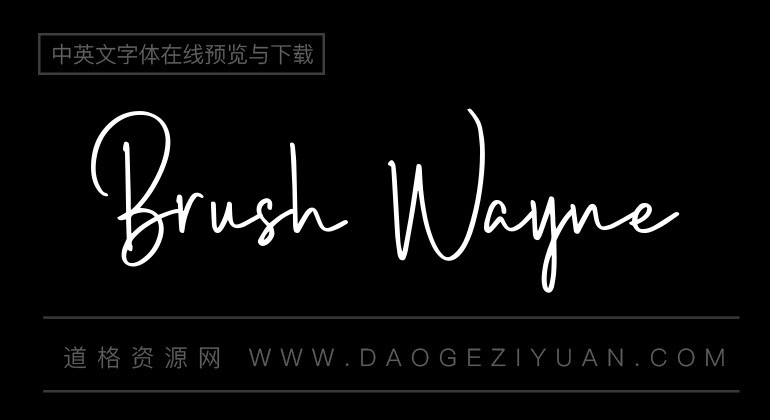
? Brush Wayne 字体是由设计师 Wayne Thompson 创作的一款手写体字体。它的特点是拥有自然的气息,每个字母都有自己独特的风格,整体比较柔和,有着温暖的感觉,是一款极具表现力的字体。它适合用于婚礼邀请函、海报、商业广告等等,可以为设计师带来很多创意。内容介绍
Brush Wayne是一款非常不错的手写艺术字体,具有很好的视觉感,适合于文化类的宣传设计、商业类品牌的广告和产品包装设计以及个性化文字排版等较多场景。